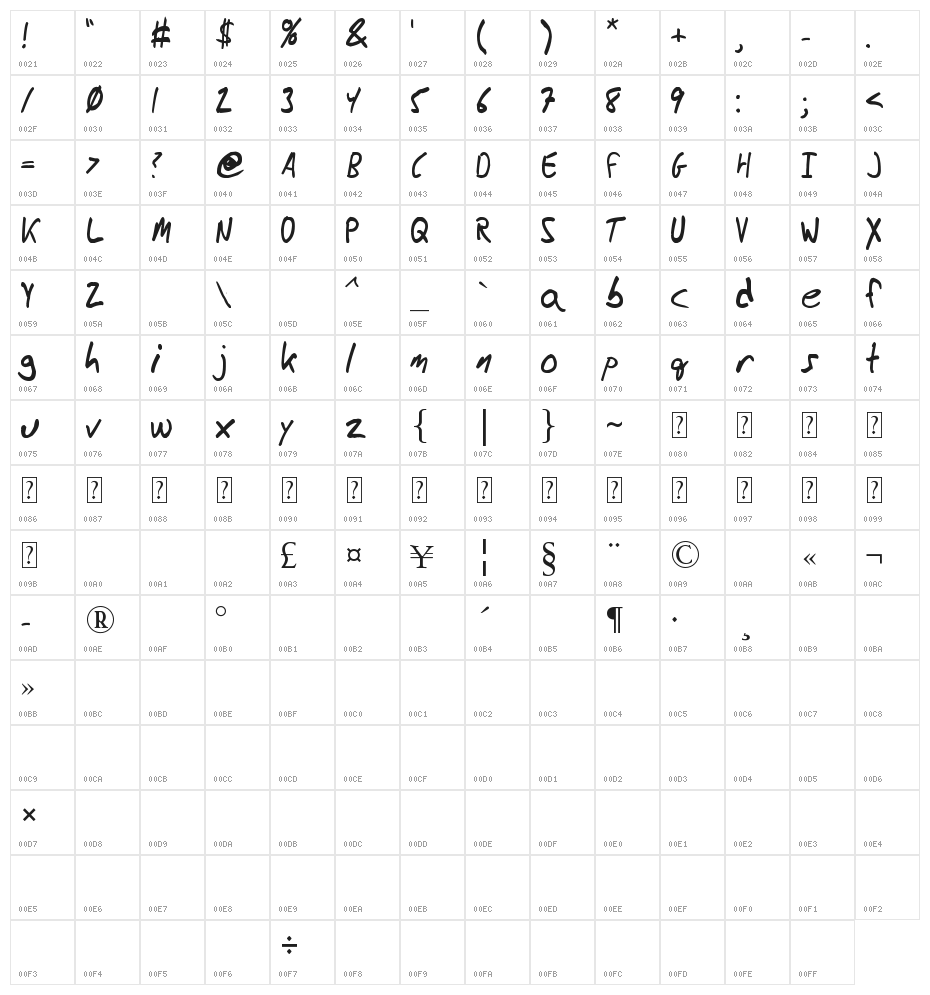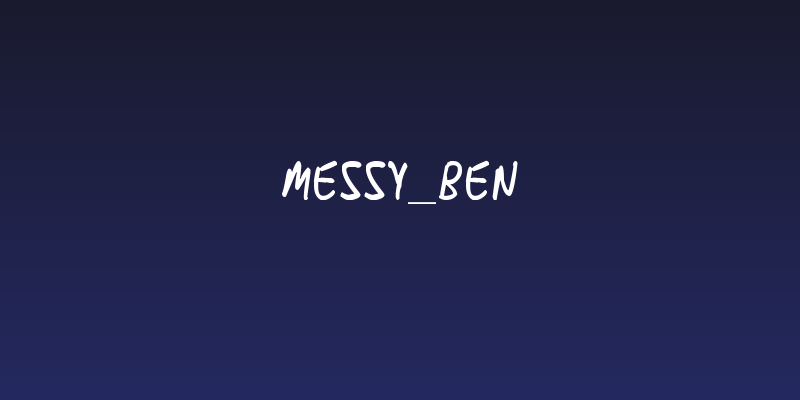
Messy_Ben Font
| Style général | Playful, Informal |
| Cas d'utilisation | Headlines, Logos, Casual Text |
| Projets proposés | Ideal for greeting cards, children's book covers, playful branding, and social media graphics. |